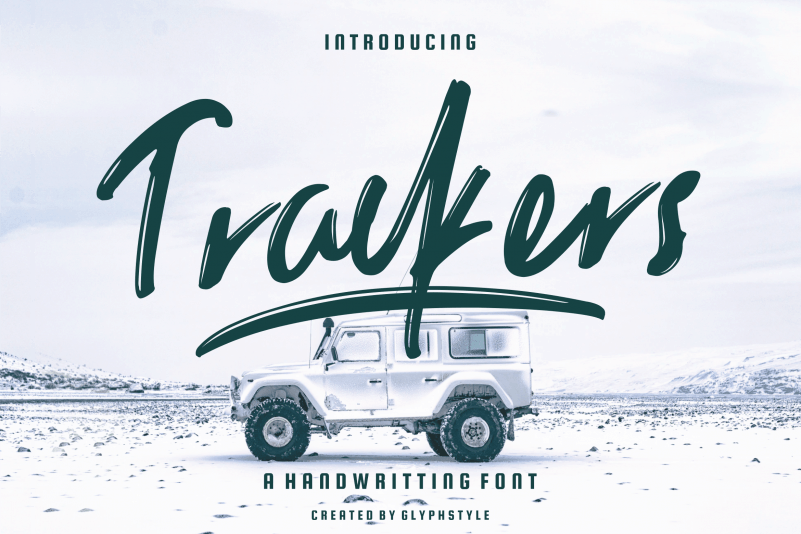
Trackers Brush Font – Download Grátis
A Trackers Brush Font é uma elegante escolha para quem busca um estilo autêntico de escrita a mão feito com canetas. Desenvolvida pela GlyphStyle, essa fonte script oferece uma textura detalhada e suavemente escura, perfeitamente projetada para ser usada em revistas, flyers ou nomes de marca, mesmo aqueles mais íntimos. Suas linhas naturais parecem como um simples traço com a mão, mantendo o realismo sem exageros. Este é um recurso gráfico que se destaca por sua praticidade e beleza natural, tornando-se uma escolha inteligente para projetos variados que buscam uma escrita cuidadosamente feita pela mão.